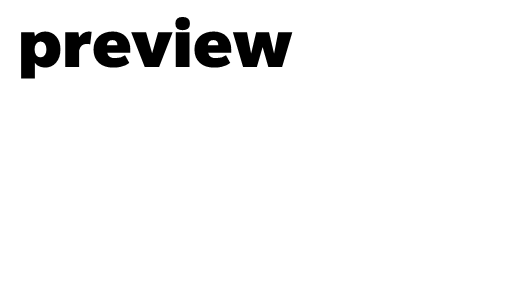
ich bin nicht so der Schriften Spezialist und komme absolut nicht dahinter welche Schriftart das ist ,
Ich tippe mal auf Helvetica, bei der der Designer die eckigen Punkte durch runde ersetzt hat. Die Punkte der Subline sehen eckig aus.
meinste es ist die Schrift "neue Helvetica 95 Black " , da sind die Punkte eckig anstatt rund.
also nochmal zusammengefasst Schrift ist "neue Helvetica 95 Black" , Pukte ersetzt durch Schriftart Slate und der Zeichen-Abstand zwischen den Buchstaben etwas verändert sodaß die Buchstaben etwas enger zusammenrücken... ist das so ??
fast, die SLATE spielt dort keine rolle, die punkte wurden bestimmt bei erstellung des logos geändert, in einem grafikprogramm.
nirgends, die Schrift existiert in diesem Sinne nicht – wie zuvor herausgefunden. Helvetiva Neue gibt es nicht zum kostenlosen Download. wenn es kostenlos sein soll, dann nimm die Arial, welche der Helvetica sehr ähnlich ist und überarbeite in einem Grafikprogramm die Kurvenpunkte etwas...wäre die günstigste Methode
hab nochmal eine andere Schrift entdeckt, die gefällt mir besser , kann mir jemand sagen was das für eine ist ??
Helvetiva Neue gibt es nicht zum kostenlosen Download. wenn es kostenlos sein soll, dann nimm die Arial, welche der Helvetica sehr ähnlich ist
und überarbeite in einem Grafikprogramm die Kurvenpunkte etwas...wäre die günstigste Methode
Bei der freien Nimbus SansL wäre auch das Erstellen einer neuen Schrift legal. Das ist zwar mehr Aufwand, könnte sich aber u.U. lohnen.